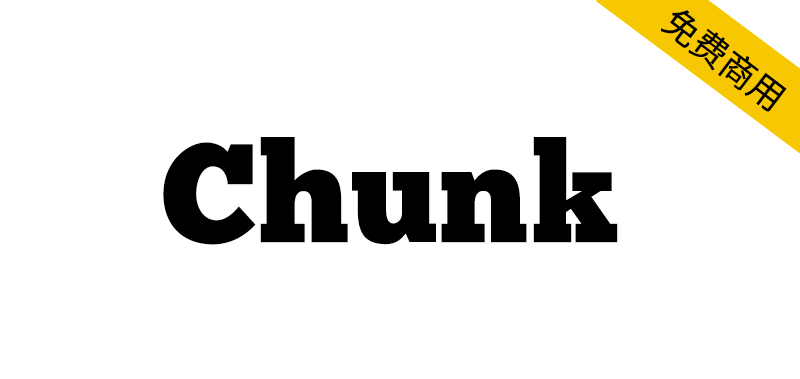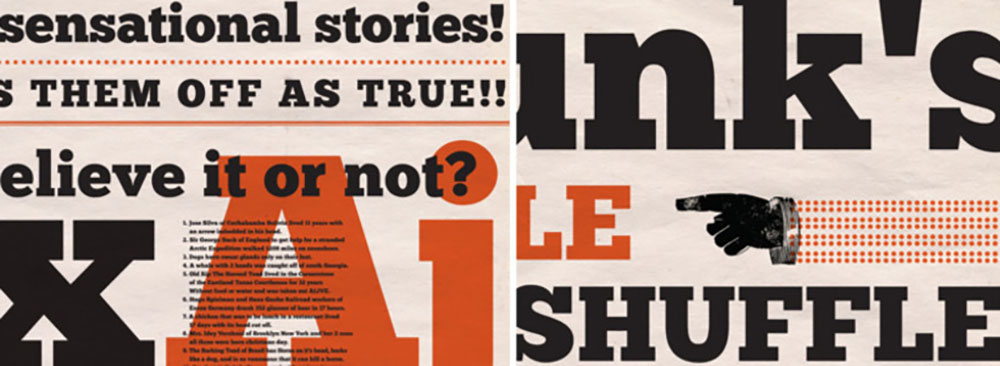
Chunk 是一款极其粗犷的粗衬线字体,其风格让人联想到美国西部古老的木刻版画、宣传海报和报纸标题。它主要用于标题展示,饱满的块状字形既奔放不羁,又经过精炼以适应现代设计需求。2014年,Tyler Finck为其增添了一种新的纹理风格,命名为Chunk Five Print,保留了原版字体的所有字符。
Chunk is an ultra-bold slab serif typeface that is reminiscent of old American Western woodcuts, broadsides, and newspaper headlines. Used mainly for display, the fat block lettering is unreserved yet refined for contemporary use.In 2014, a new textured style was created by Tyler Finck called Chunk Five Print. It contains the same glyphs as the original.